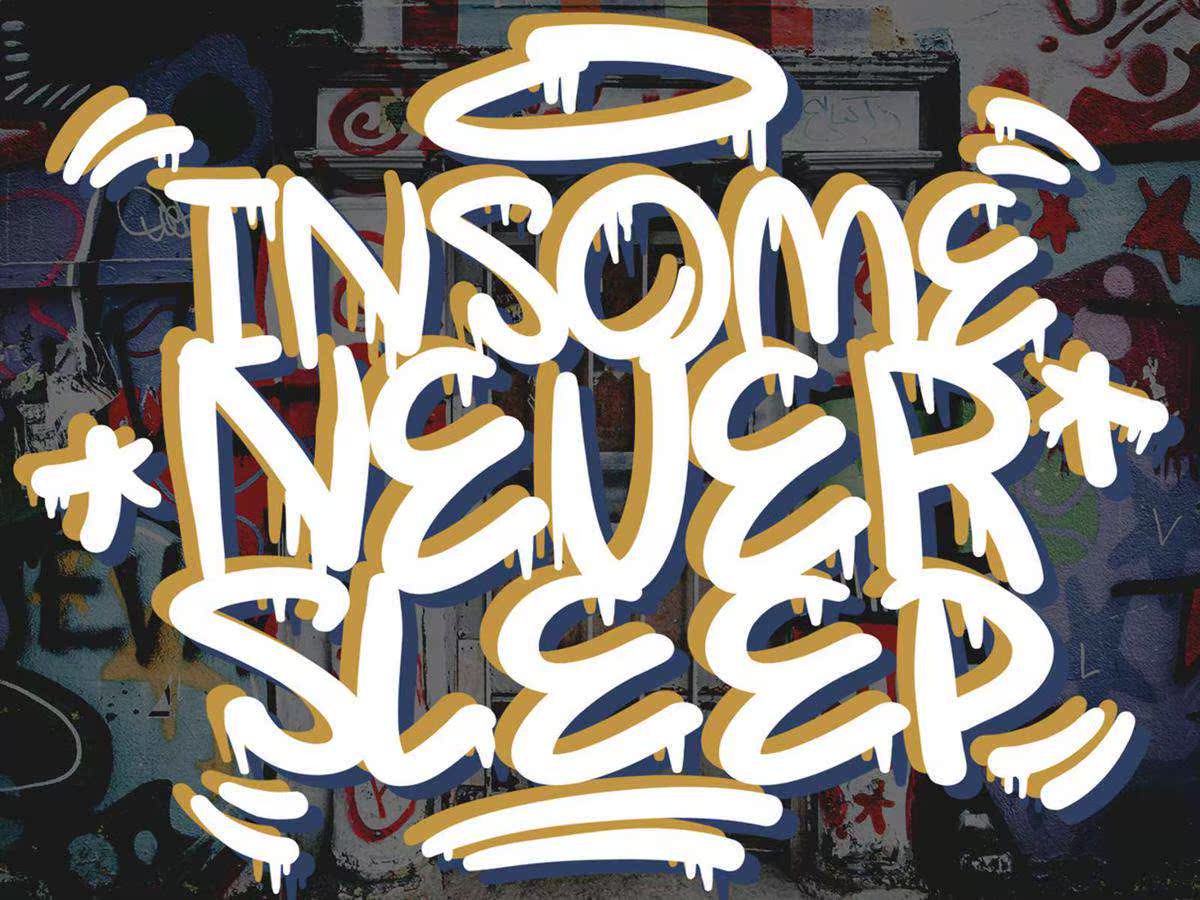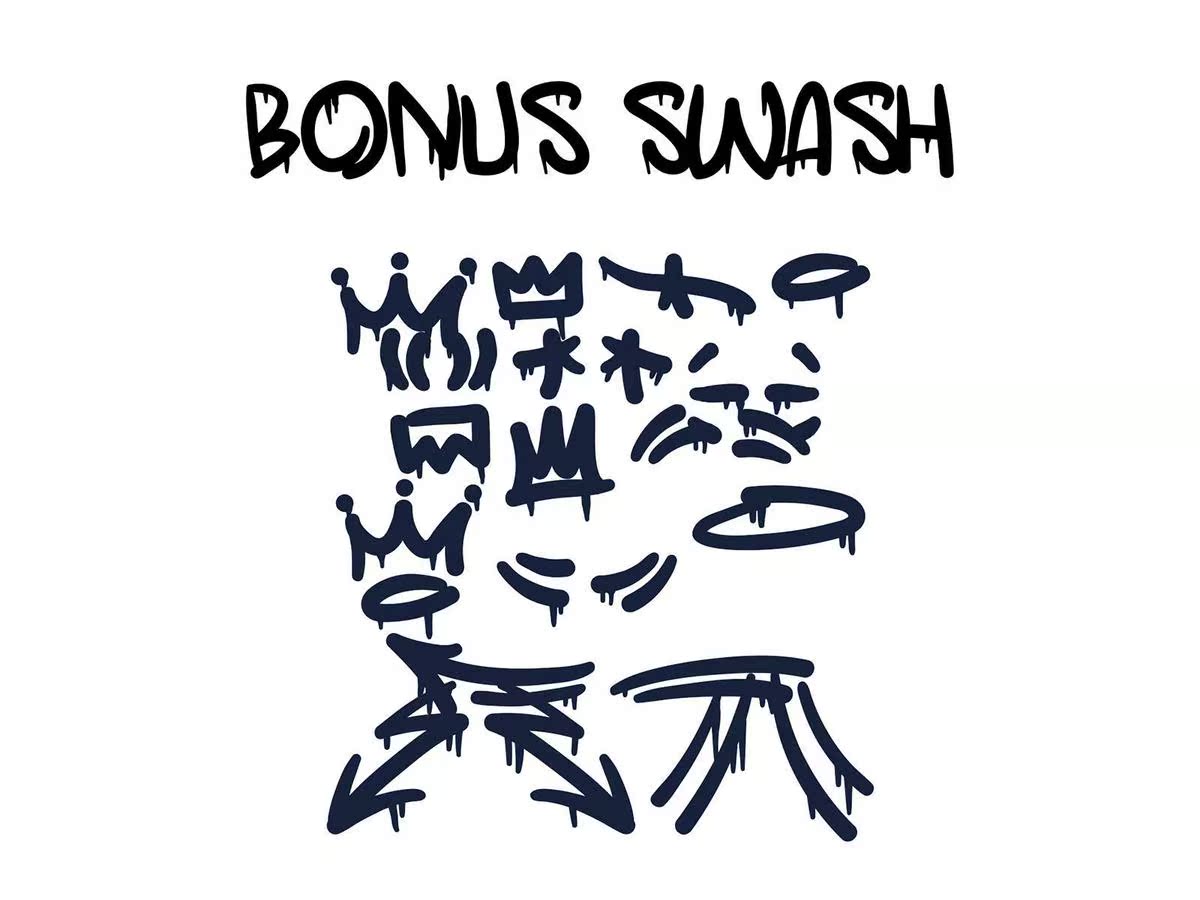
下面的背景是来自Apriellat的新字体,优雅的表情字符集。要创建美丽的组合,只需将大写字母和小写字母混合在一起,并使用omeswash。下面的背景激发了Estreet上的涂鸦风格。下面的背景是来自Apriellat的新字体,优雅的表情字符集。要创建美丽的组合,只需将大写和小写字母混合在一起,并将其涂鸦。下图显示了桌面上的涂鸦风格。